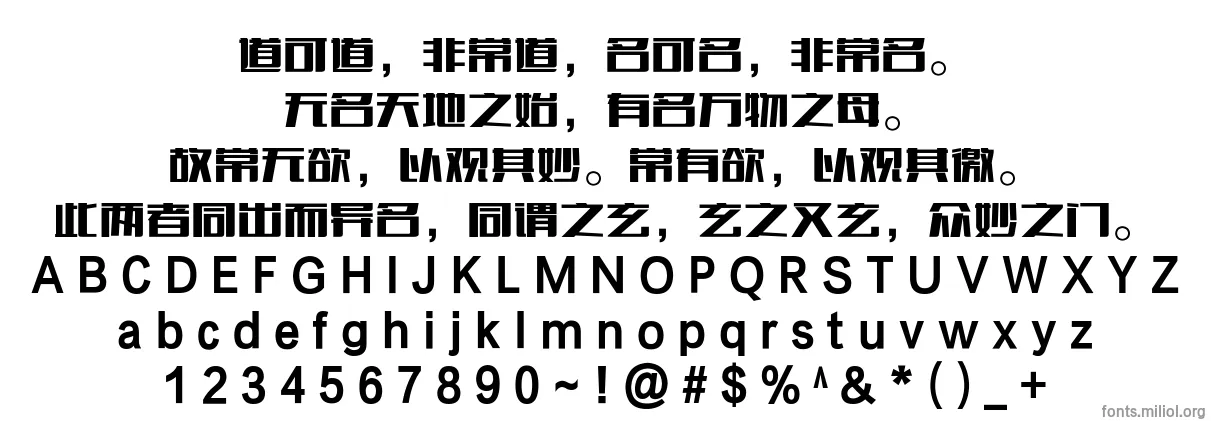
《方正粗谭黑简体:现代设计中的经典字体》
方正粗谭黑简体(FZTanHeiS-B-GB)是方正字库推出的一款极具辨识度的无衬线字体,其设计融合了传统黑体的稳重与现代字体的简洁。这款字体笔画粗壮有力,转角处略带弧度,既保留了印刷体的规整性,又通过细节处理赋予文字独特的视觉温度。
作为GB2312编码的标准字体,它完美支持简体中文常用字符,在标题设计、品牌标识、广告宣传等场景中表现尤为突出。字体的加粗特性使其在小字号下仍能保持清晰度,而放大后更显力量感,特别适合需要强视觉冲击力的设计项目。
设计师常选用这款字体传递权威、可靠的信息,其均衡的字面结构和适度的字间距让排版更具节奏感。无论是数字屏幕还是印刷物料,方正粗谭黑简体都能保持稳定的表现力,成为中文字体库中经久不衰的选择。